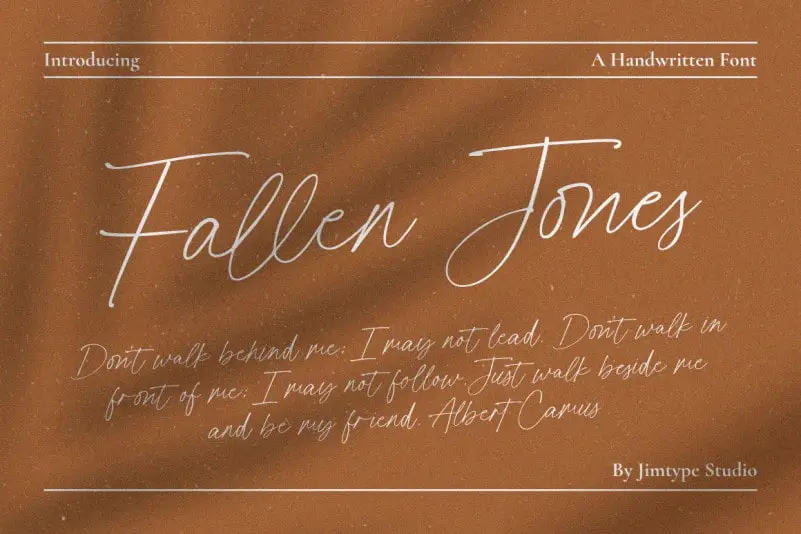
Fallen Jones Script Font – Download Grátis
Descubra a beleza única e sofisticada do Fallen Jones Script Font, uma elegante tipografia escrita à mão ideal para designers apaixonados pelo detalhe. Esta fonte casual traz um toque luxuoso que será uma adição maravilhosa ao seu acervo de tipos. Através dos traços naturais e fluidos, você pode experimentar a personalidade única e sofisticada desta fonte, sem dúvida uma escolha perfeita para gráficos profissionais ou projetos pessoais. Que tal adicionar um pouco de elegância ao seu próximo projeto com este belo tipo à mão?